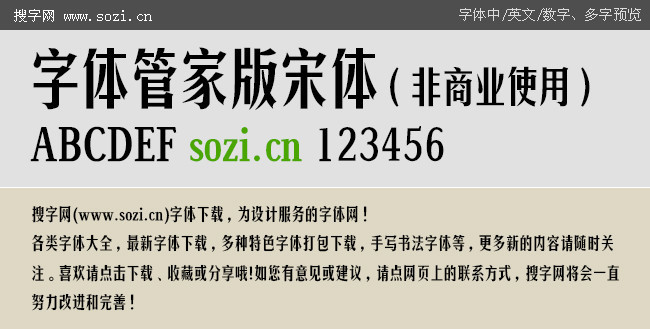
字體管家版宋體(非商業(yè)使用)
搜字網(wǎng)給大家提供一款字體管家版宋體(非商業(yè)使用)中文字體下載,該字體造型筆直細長,經(jīng)過加黑加粗處理,,比一般的字體更加顯眼,適合海報設(shè)計、包裝畫冊等宣傳廣告等應(yīng)用(此字體為個人非商用版,商用可以聯(lián)系QQ:1006760504)。